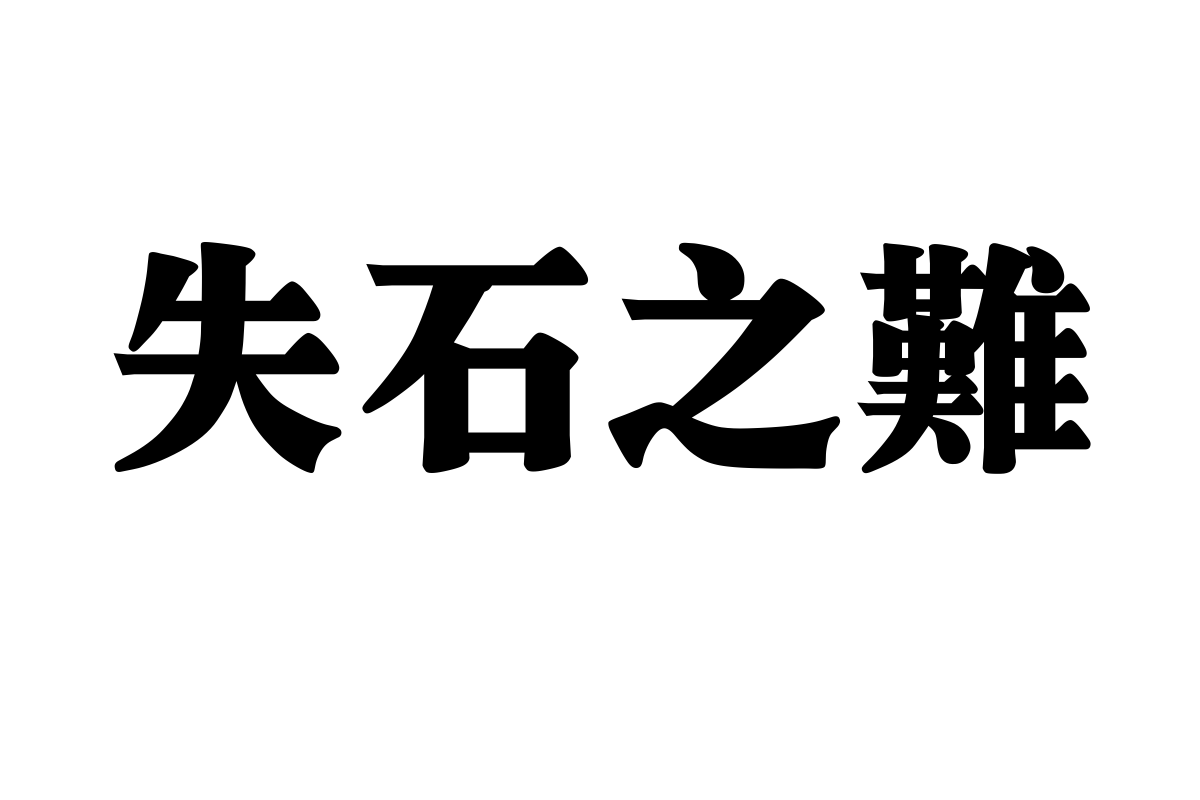
汉仪超粗宋繁字体是一款专为中文书写设计的粗体字体,具有强烈的视觉冲击力和辨识度。这款字体采用了传统的宋体结构,但通过增加笔画粗细来达到超粗的效果,使得字体更加醒目、有力。
汉仪超粗宋繁字体的特点如下:
1. 粗体设计:字体的笔画粗细明显,给人一种强烈的视觉冲击感,适合用于标题、广告、海报等需要突出显示的部分。
2. 易读性:虽然笔画粗,但汉仪超粗宋繁字体的字形结构规整,易于阅读和识别,不会因为笔画过粗而影响文字的可读性。
3. 适用范围广泛:这款字体适用于各种印刷品、电子屏幕显示等多种场合,无论是在报纸、杂志、书籍还是网页、移动设备上,都能展现出其独特的魅力。
总之,汉仪超粗宋繁字体是一款功能强大且实用的粗体字体,适用于多种场景,能够满足不同用户的需求。